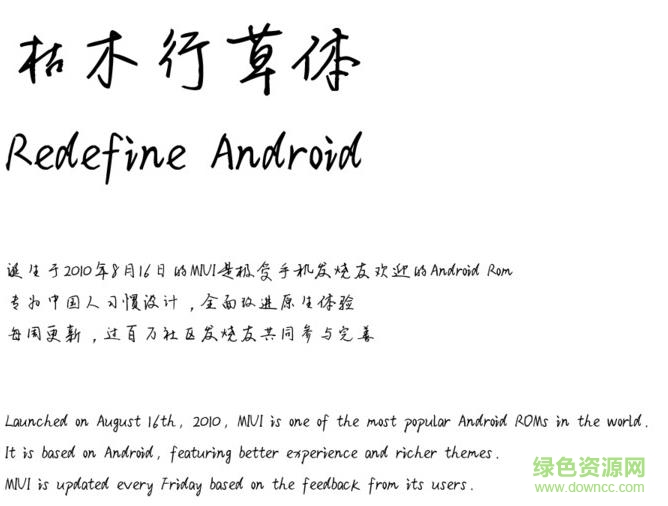
枯木行草體字體
枯木行草體這款字體的使用將讓你感受和到十分鮮活的氣息,能夠?qū)崿F(xiàn)字體樣式的枯木逢春效果,讓你感受到極致享受的字體使用體驗(yàn),是95后的小伙伴們打造的一款精美字體!
枯木行草體介紹
枯木逢春猶再發(fā),人無(wú)兩度再少年。簡(jiǎn)介:該字體出自95后小鮮肉,字體老練程度與顏值嚴(yán)重不符,不要以為少年就與成熟穩(wěn)重絕緣,見(jiàn)字如見(jiàn)人,字形穩(wěn)健雄偉、獨(dú)具匠心。少年強(qiáng)則國(guó)強(qiáng)!
能夠讓人一見(jiàn)傾心,這款字體十分不錯(cuò)的,給你在不同場(chǎng)所都能夠獲得最佳的視覺(jué)效果!